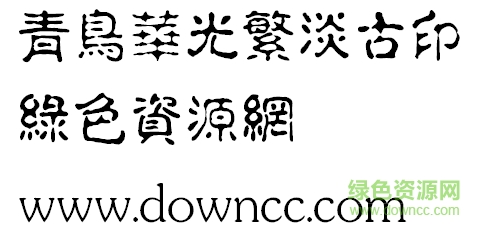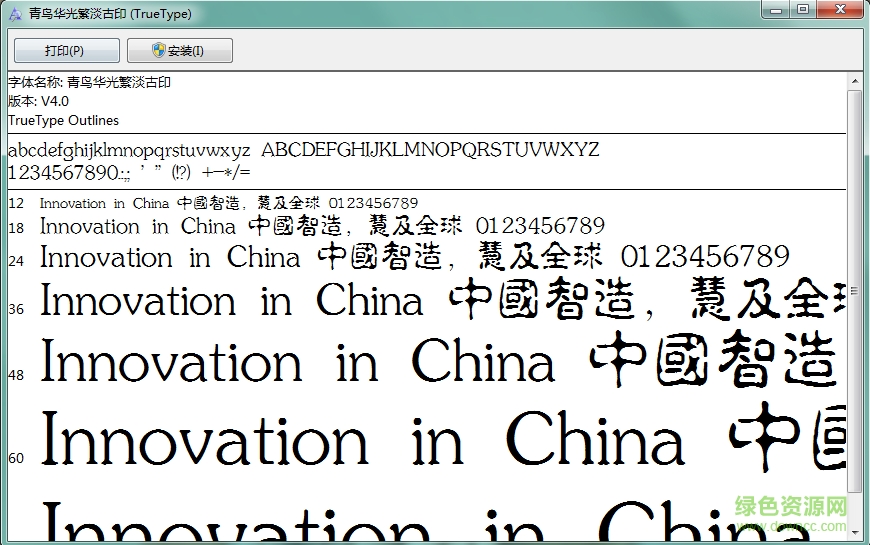
青鳥華光繁淡古印是一款輸入簡體自動(dòng)轉(zhuǎn)換成繁體的青鳥華光字體,古印體有著清秀柔和的筆觸,很有古風(fēng)韻味和飄逸之美,喜歡的朋友來綠色資源網(wǎng)即可免費(fèi)下載哦!
青鳥華光繁淡古印作為華光系列的古印字體,繼承了造型美麗、風(fēng)格高壓、行書飄逸的特點(diǎn),讓你的藝術(shù)創(chuàng)作、平面設(shè)計(jì)別有一番風(fēng)味。